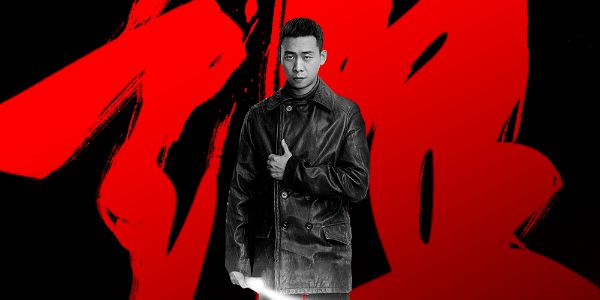
谁说汉字不好排版?
相信大家都听过这样的观点:英文排版就是好看,怎么排都很高级。只要把英文海报换成中文就瞬间就LOW了。。。。等等。
从视觉上来看,英文和汉字的字形特点很不一样。英文字符结构简单,比较几何化。
可以看得出,单个的英文字母,都是非常接近一个最基础的几何体图形的,所以阅读的时候它是单词,不阅读的时候,它是图形。
而汉字是方块字,排版起来,像多个方块的长条,没有英文的凹凸有致几何感和有节奏感。
但是!
单独看每一个字都有着很优美的结构,你认真去看任何一个稍稍有点结构的汉字,都是非常的有艺术感的,汉字的排版难度确实要稍微高点,但是绝不是那些人说的:你换汉字就肯定难看了。只有会用,汉字不比英文的视觉差的~
所以,虽然汉字的排版没那么容易,但是只要掌握了正确的方法,汉字的独有的结构和线条,可以使我们的版面设计自带一种独特的东方美感。下面我就给大家分享几招好用的汉字排版手法。
汉字之所以排版难,最主要的原因之一,就是汉字都是方块字,组合到一起容易看起来没有节奏变化。所以让排版看起来更有节奏,我们可以加强对比,将标题放大,与其它文字形成强烈的对比。
如果我们的画面主体比较弱,或者没有图像主体,那放大的文字可以直接当作画面主体来用。
来看看实操案例,我们以户外为主题,做一张海报。
第1步,
抠一张户外的人物图。
第2步,
在画面底部添加地面的场景,让车子与地面融合。
第3步,
添加天空的图片素材,这样我们整个场景就拼接完成了。
第4步,
统一整个场景的色调。
第5步,
打上标题文字,大致确定位置和大小。
第6步,
因为我们的标题很大,所以选择粗壮有力量感的字体,再添加一些微小的变化,可以让它看起来更有设计感。
第7步,
完善好其它文案信息。
OK,完工!
前面我们说了,方块的汉字排版容易看起来呆板,而书法字体则刚好弥补了这一不足。书法的线条张力,还有墨的飞白效果,都能给设计带来强大的视觉冲击力。
书法字体不仅能让排版看起来气势十足,它的线条更是充满了意韵,能瞬间让人GET到中化传统文化的美感。
来看看实操案例。要说到最近谁主演的剧最火,估计张译称第二,没有敢称第一了,下面我们就来做一张《他是谁》的海报。
第1步,
抠一张帅帅的剧照。
第2步,
去色,方便我们后续进一步处理。再给人物加上投影。
第3步,
改成深色渐变背景,让场景有点空间感。
第4步,
用书法字体打上海报标题。
第5步,
为了让主题更加明确突出,把前面两个字缩小,着重突出“谁”。
第6步,
用画笔在文字的边缘添加毛笔的笔触以及墨汁散开的效果,增加视觉冲击力。同时将背景换成红色到黑色的渐变,呼应标题的色调。
第7步,
排版好其它文案信息。
OK,完工!
在不影响文字识别性的前提下,将文字的局部,或者部分文字模糊掉,与清晰的部分形成虚实对比,可以让文字排版形成很好层次感。
也可以把单独的笔划提取出来,做成模糊的效果,让文字形成前后的立体效果。
来看看实操案例。
最近,韩剧《黑暗荣耀》到刷屏,复仇这种最原始最朴素的主题果然还是最吸引人的,我们就以它为主题来一张海报。
第1步,
找一张两位女主角对峙的剧照。
第2步,
将图片放大,聚焦到演员的脸部线条。
第2步,
为了让画面体现出剧情的冲突,把主色调换成黑色与明亮黄色的对比,给人一种紧张不安的感觉。
直接叠加一个黑色到黄色的渐变映射,就可以做出这种效果了。
效果如下:
第3步,
打上标题文案。
第4步,
把标题切分成两部分,形成大小对比。
第5步,
将大字模糊处理,再排版好其它文案信息。
OK,完工。
汉字经过几千年的发展,每一个笔划都是一个完整的视觉符号,有着微妙的变化与平衡,这种美感是独一无二的。
就是是把文拆掉,依然能感受到汉字结构中所蕴含的平衡美感。
黄海的这张经典作品,就是将文字拆散,打破原有的视觉印象,将汉字笔划的独特美感巧妙的融合到了海报的主题中。
以后不要傻乎乎地人云亦云:你试试换中文就不好看了。
以你的技术,换啥字上去都难看。